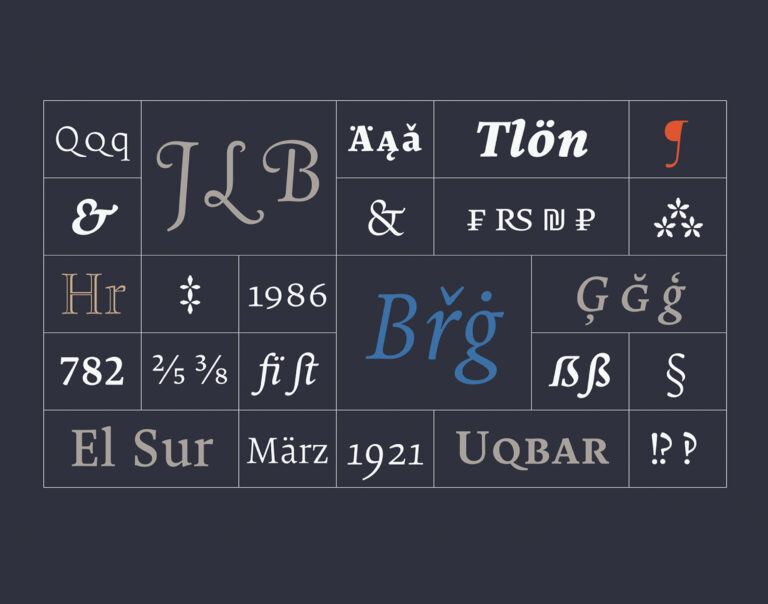
Borges de Alejandro Lo Ceslo para Pampatype
La finalidad primordial de la tipografía para cuerpo de texto es ser leída. La legibilidad es el caballo de batalla de las tipos de texto. Estas letras reclaman silencio, incluso lentitud. Son las letras que habitan sobre todo en los libros. Las primeras tipografías que existieron.
Una tipografía para cuerpo de texto es un sistema perfectamente organizado con una finalidad concreta, la composición de una pieza editorial que sea cómoda y fácil de leer. No todas las fuentes tipográficas sirven para todo. La tipos de textos están expresamente diseñadas para componer grandes masas de texto que un lector medio sea capaz de leer sin excesivo esfuerzo. Una fuente de texto, por tanto, debe disponer de todos los elementos para estos menesteres, es decir, los caracteres necesarios para cubrir todas las necesidades que requiere el diseño editorial: cursivas, negritas, versalitas, distintos tipos de numerales y toda la batería de caracteres necesarios en un texto, incluidos los alfabetos más usados, no solo el latino. Por lo tanto no debemos olvidarnos nunca, antes de afrontar un trabajo editorial, de comprobar que la fuente tipográfica escogida dispone de todas las prestaciones que el proyecto requiere.
Vamos a repasar siete ejemplos recientes de tipografías para cuerpos de texto de diferentes extensiones que nos han parecido especialmente interesantes.
Borges, de Pampatype
Por regla general no hay que dejarse influir por el nombre de las fuentes tipográficas, porque entre lo que el nombre sugiere y las características formales de la tipo pueden mediar grandes distancias. No es el caso de Borges, pues se trata de una tipo de estilo clásico para cuerpo de texto.
Su autor, Alejandro Lo Celso, declara que se trata de un «humilde homenaje» a su genial compatriota Jorge Luis Borges, una de las cimas literarias del siglo XX.
Borges —la tipo— se inspira, según Lo Celso, en la técnica de escritura de Borges —el escritor—, que es «la de un orfebre minucioso e incansable, que busca sin cesar la palabra perfecta», por lo que «sugería una forma de letra limpia y económica». Es decir, una tipo de letra para sumergirse con todas las garantías de comodidad lectora en la erudición y las fantasías sin límites del autor de El libro de los seres imaginarios.
Punta, de Hot Type
Una tipo para cuerpo de texto puede poseer perfectamente cualidades suficientes para funcionar también a gran escala. Por razones obvias, donde mejor se aprecian las características formales de cualquier tipografía es en tamaño grande.
Punta, del estudio croata Hot Type, posee cierto dramatismo en sus proporciones, quizá por el carácter escultórico de su construcción, angulosa y contrastada, lo que la convierte en una fuente altamente versátil. Legible, limpia y con la justa dosis de personalidad, ofrecerá óptimos resultados desde los titulares hasta textos de media extensión, por lo que puede ser ideal en productos editoriales como revistas o fanzines.
Punta en uso: Vizkultura Magazine
Zenon, de C.A.S.T.
Zenon, de los italianos C.A.S.T., es una tipo para cuerpo de texto construida a partir de una síntesis o ideal de las tipos renacentistas y adaptada a los modos tipográficos del siglo XXI.
Concebida tanto para pantalla como para impresión, Zenon posee un espíritu orgánico, propio de las tipos que mantienen intacta la huella de la mano en su personalidad. Su textura en página produce la agradable sensación propia del equilibrio entre lo manual y lo artificial, lo artesanal y lo industrial.
Gestura Text, de Sociotype
Perteneciente a una amplísima familia, de Gestura Text, sus hermanas Headline y Display, y sus creadores Sociotype hablamos recientemente en este post con motivo de la publicación de Sociotype Journal, un espécimen tipográfico y simultáneamente una revista cultural.
Gestura Text está concebida como una tipo que facilita una lectura cómoda, gracias a una legibilidad clara y a una textura uniforme y sedosa en la página.
Dejanire, de Retype
A partir de una anónima fuente tipográfica hallada en un espécimen francés del siglo XVIII, el diseñador tipográfico Ramiro Espinoza ha realizado un ejercicio de estilo, depurando y estilizando las formas de aquellas viejas letras para construir una nueva fuente tipográfica editorial.
Nítida, fresca y limpia, Dejanire toma su nombre de la princesa Deianira, esposa de Heracles en la mitología griega. La amplitud de la propuesta, compuesta por dos subfamilias, Headline y Text, la convierte en una opción altamente versátil para toda clase de productos editoriales, tanto en pantalla como impresos.
Bureau, de Frost
La fundición digital británica Frost presentó Bureau, una serif de aires clásicos, hechuras renacentistas y espíritu contemporáneo. Curvas y ángulos conviven en su construcción, detalles que la dotan de una sugerente personalidad que puede dar mucho juego en tamaños considerables, aunque su vocación está en dar forma a textos de aspecto agradable.
Feature, de Commercial Type
Feature, diseñada expresamente para T: The New York Times Style Magazine en 2018, sale ahora a la venta pública. Se trata pues de una fuente tipográfica concebida específicamente para proyectos editoriales, en la línea de tipos ya clásicas como Times New Roman y NTY Imperial, con las que comparte ADN, pero marcando su propia personalidad. Al fin y al cabo fue diseñada para un magazine de cultura y lifestyle, por lo que su impronta está clara.
Feature, originalmente diseñada para T: The New York Times Style Magazine